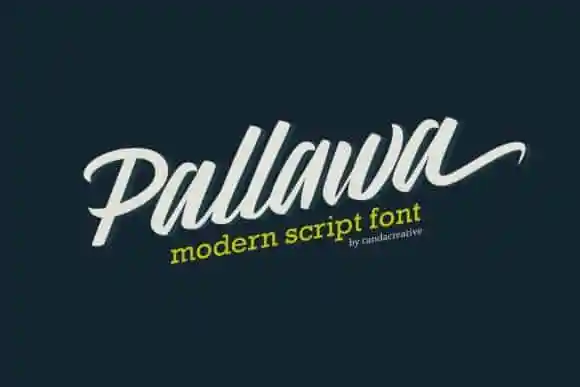
Pallawa Modern Script Font – Download Grátis
Introduzimos a fonte script moderna Pallawa, uma tipografia com estilo de calligrafia. Esta é uma fonte monoline que leva à uma aparência vintage. Com belas alternativas de caracteres e formas sutis para dar um aspecto vintage ou esportivo aos seus designs, Pallawa oferece flexibilidade ao permitir que qualquer ideia criativa seja transformada em arte verdadeira. Esta é uma fonte casual e encantadora projetada pela Candacreative. Possui lindas ornamentações e ligaturas que a tornam versátil para aplicativos como o Instagram ou projetos DIY de calligrafia, proporcionando um toque único à qualquer design. Seja você uma pessoa mais formal ou casual, Pallawa traz beleza e personalidade ao seu trabalho de gráfica.